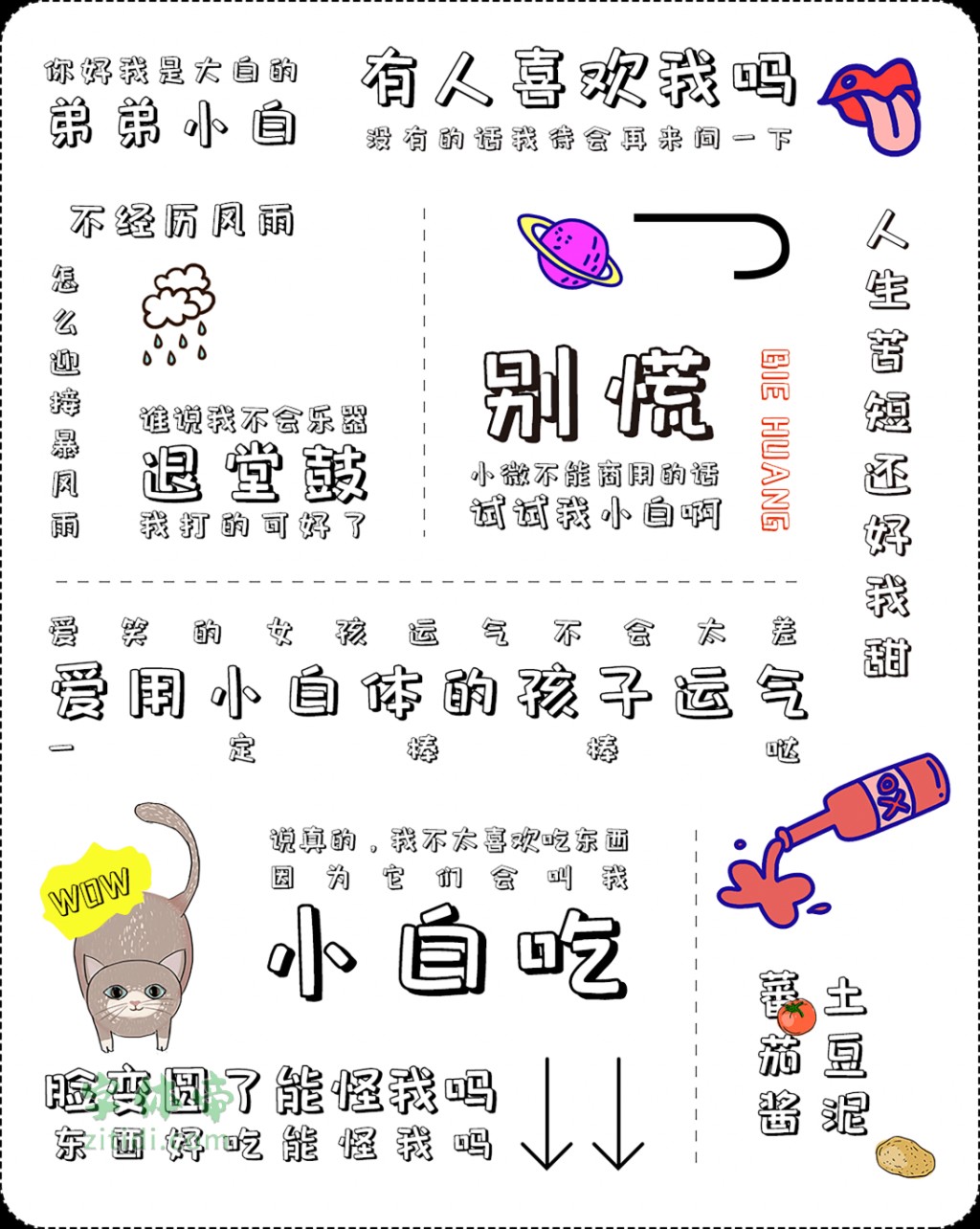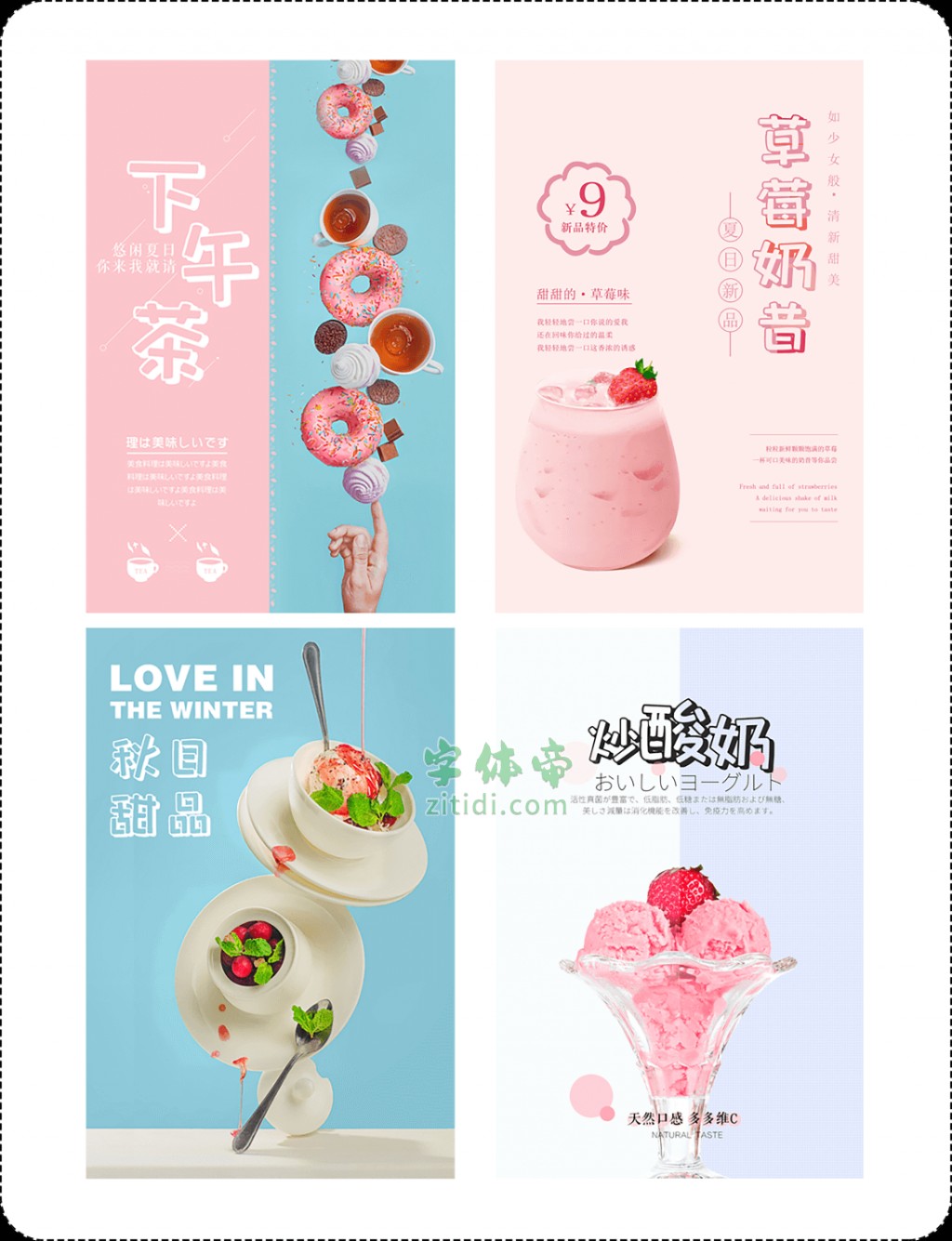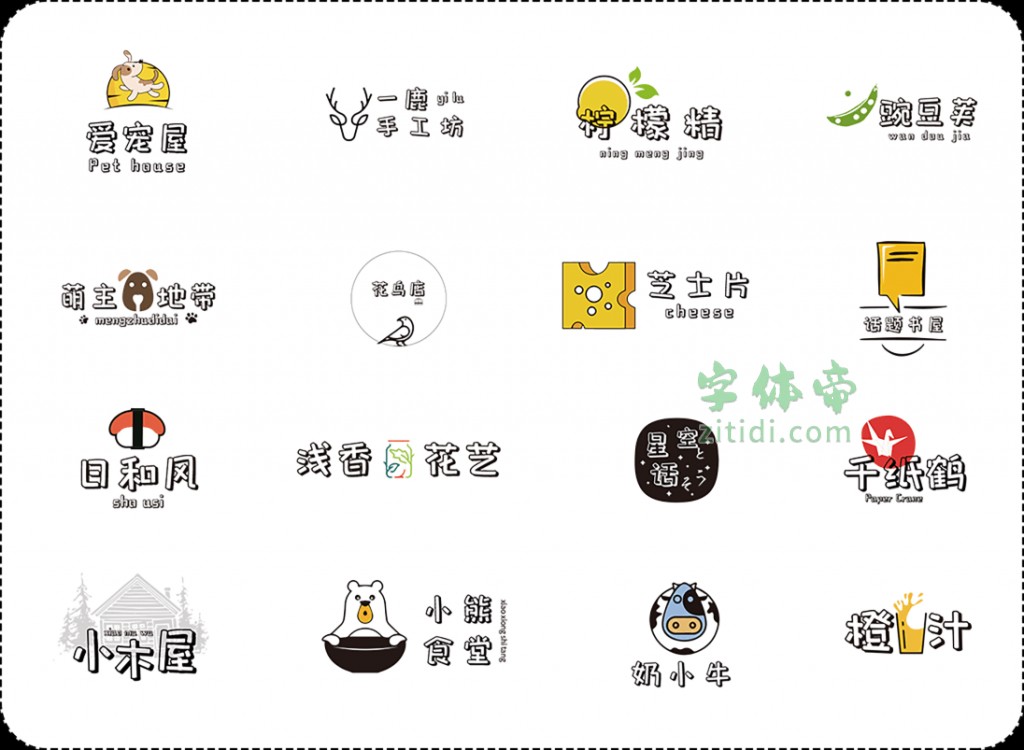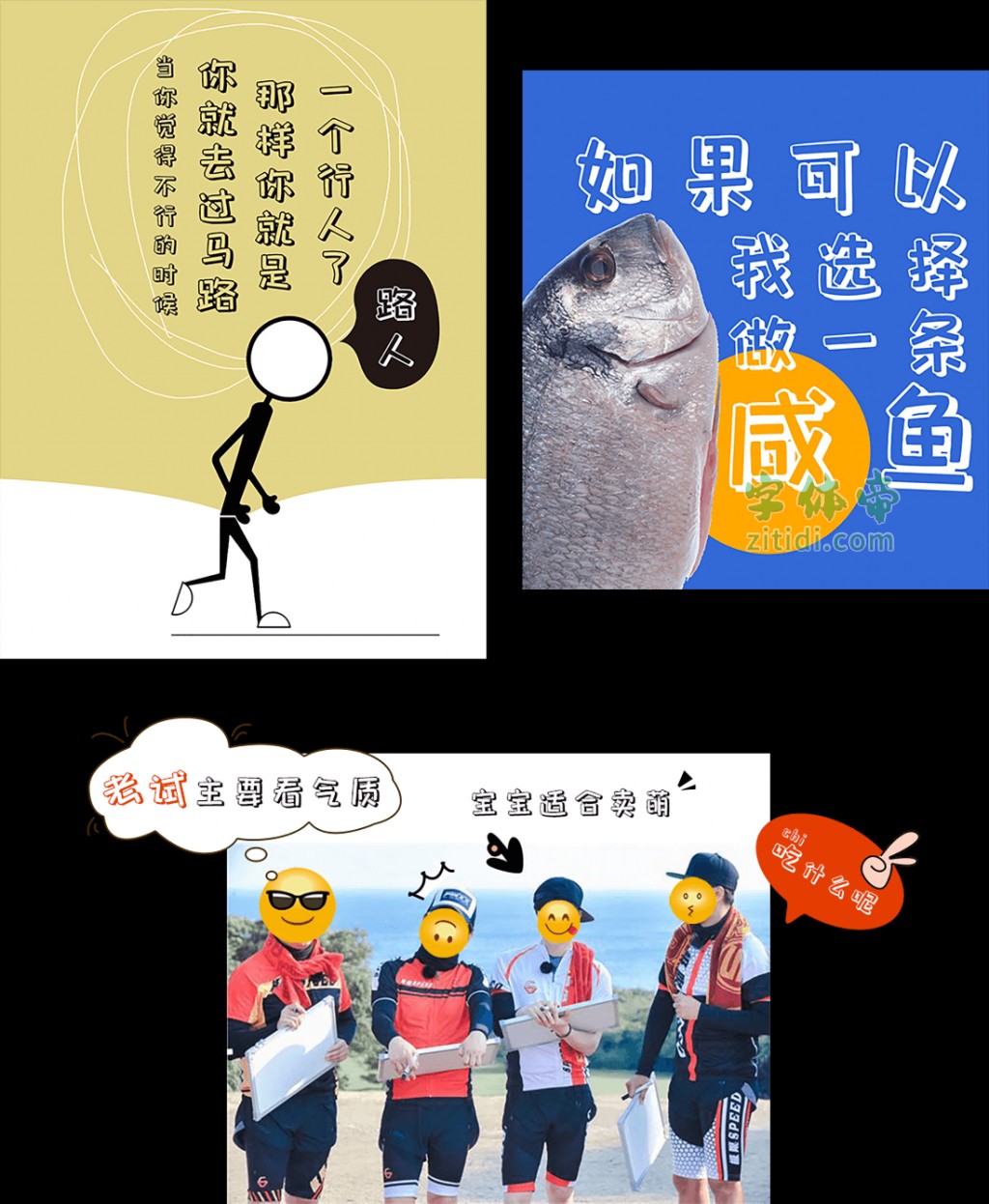
字体背景
「 包图小白体 」 ,原名为小白,是字体视界团队2018年创作的一款字体,推出半年来一直广受设计师喜爱。现由包图网与字体视界合作,正式更名为:包图小白体,字体版权归包图所有,并将字体作公益开源,向全社会开放下载并可免费商用(包括个人及企业商业用途)。
字体特色
「 包图小白体 」 , 定义为一款简单可爱的创意字体。在字形笔画上去除了折笔的弧形,换之以平直的笔画,竖弯钩转为竖折,同时弱化了钩笔画,省去了许多笔画末尾的小尾巴,显得更加直白可爱。粗短的笔画,像柯基的小短腿,相比细长的字体能给人更多的轻松感。整体形态采用了镂空的制作技巧,增强了字体的立体感,适合用于品牌标志、海报、包装、影视综艺、游戏、漫画等场景。
「 包图小白体 」 采用GB2312编码,共收容7707个字符,包含6763个简体汉字、110个大写字母、139个小写字母、102个数字、95个标点符号、其他特殊类符号288个、其他字母210个(包含日文平假名片假名)。